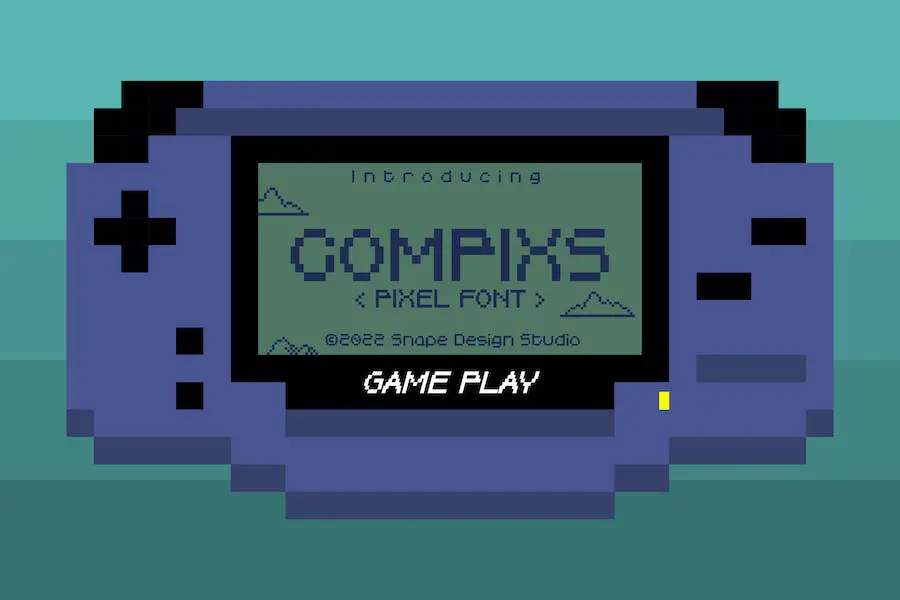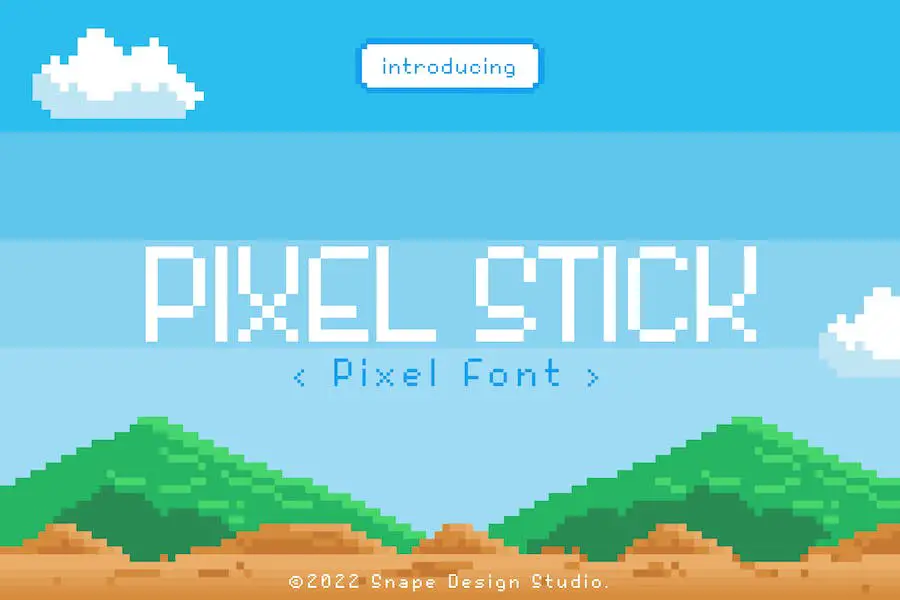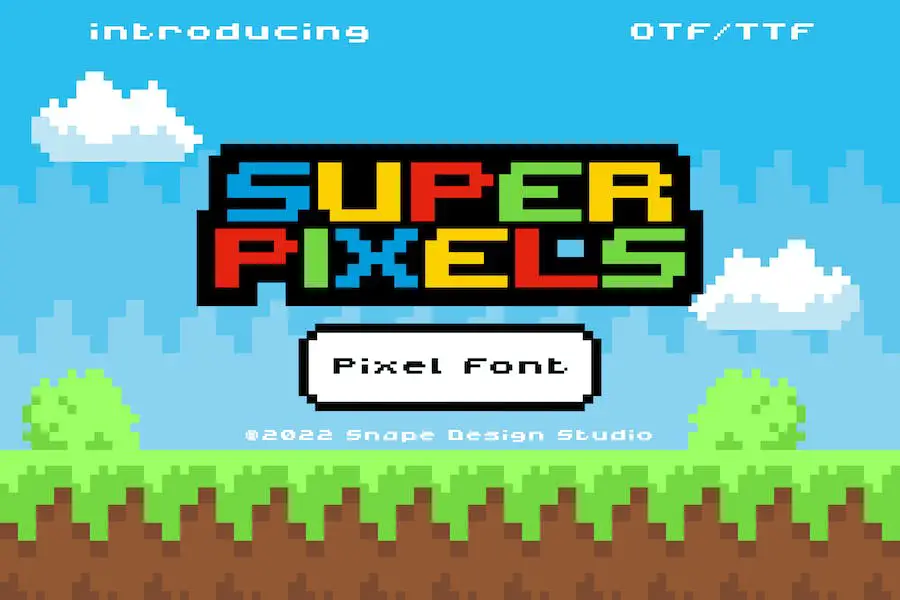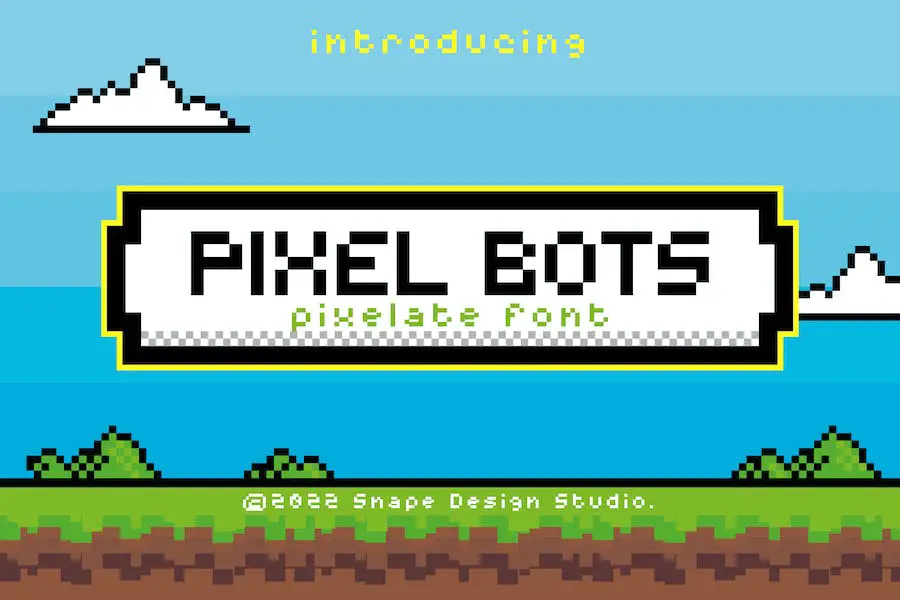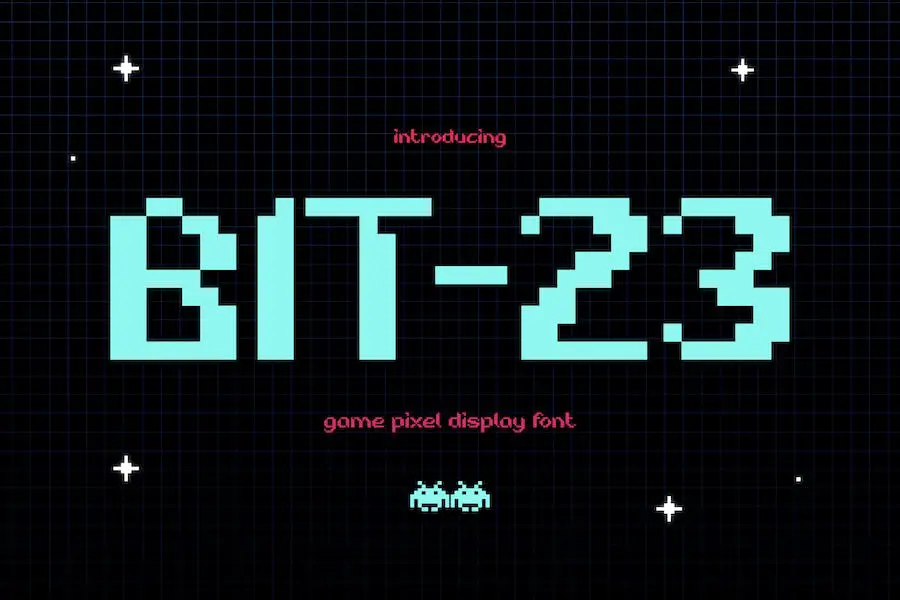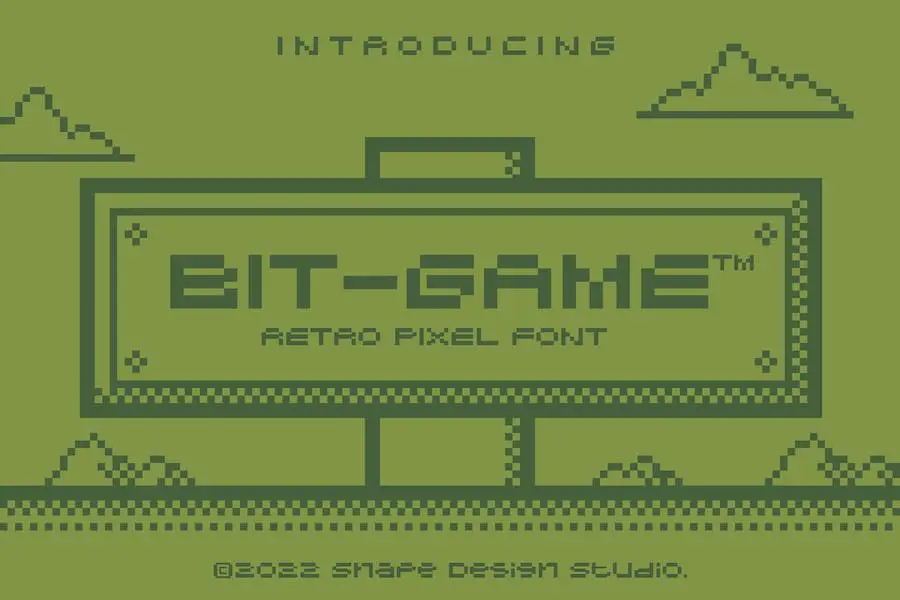
8 Bit Yazı Tipinden başkasına bakmayın! Bu blog yazısında 8 bitlik yazı tiplerinin dünyasını ve bunların tasarımlarınızı bir sonraki seviyeye nasıl taşıyabileceğini keşfedeceğiz. İster deneyimli bir grafik tasarımcı olun ister yeni başlıyor olun, bu yazı tipleri kesinlikle dikkatinizi çekecektir.
Şimdi "8 bitlik yazı tipleri tam olarak nedir?" diye merak ediyor olabilirsiniz. Peki, açıklayayım. 8bit yazı tipleri, retro video oyunlarının nostaljik çağından ilham alan yazı tipleridir.
Eski konsollarda klasik oyunlar oynayarak geçirilen saatleri hatırlatan pikselli karakterleri ve canlı renkleri düşünün. Bu yazı tipleri her türlü tasarıma benzersiz ve eğlenceli bir dokunuş katarak izleyicinin dikkatini anında çeker.
Bu yazıda 8 bitlik yazı tiplerinin dünyasına dalacağız ve kendi projelerinizde kullanabileceğiniz bazı inanılmaz örnekleri sergileyeceğiz.
Ayrıca bu yazı tiplerini kullanmanın, nostalji duygusu uyandırma yetenekleri ve çeşitli tasarım stillerinde çok yönlülükleri gibi faydalarını da tartışacağız. Birlikte bu 8 bitlik yazı tipi yolculuğuna çıkarken tasarım oyununuzun seviyesini yükseltmeye hazır olun!
En İyi Premium 8 Bit Yazı Tipleri
Tasarım projelerinize nostaljik bir dokunuş ve pikselli çekicilik mi katmak istiyorsunuz? En iyi premium 8 bit yazı tiplerinden özenle seçilmiş seçimlerimizden başka bir yere bakmayın. Tasarımlarınızı bir sonraki seviyeye taşıyacak mükemmel yazı tiplerini keşfetmek için bu makaleye dalın.
Para Ding Dong
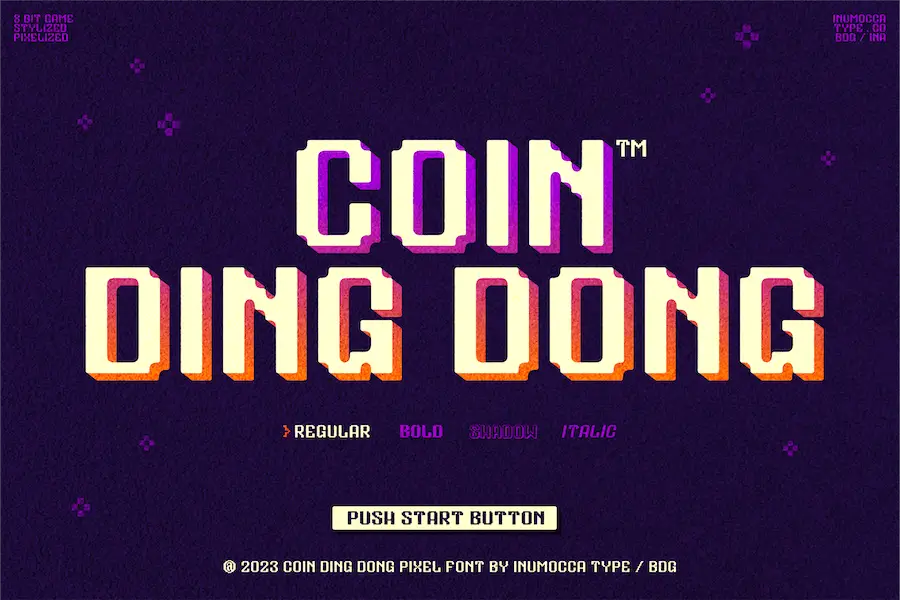
Coin Ding Dong, tasarım projelerinizi bir sonraki seviyeye taşıyacak muhteşem bir piksel yazı tipidir. Çok dilli karakterleri, benzersiz glifleri ve PUA kodlamasıyla bu yazı tipi sonsuz yaratıcı olanaklar sunar.
8 bitlik oyunların nostaljik dünyasından ilham alan Coin Ding Dong, güzel stilize edilmiş pikselleriyle sizi çocukluğunuza götürüyor. Tıpkı bir kumar makinesinde oynamak gibi, bu Google 8 Bit yazı tipi
eğlence ve heyecan dolu anıları geri getirir.
En iyi yanı Coin Ding Dong'un kolay olmasıdır
kullanmak. PUA kodlaması ile sunduğu tüm özel karakter ve sembollere sorunsuz bir şekilde erişebilirsiniz. Sınırlamalara elveda, sonsuz yaratıcılığa merhaba deyin.
Alpharush – retro oyun yazı tipi
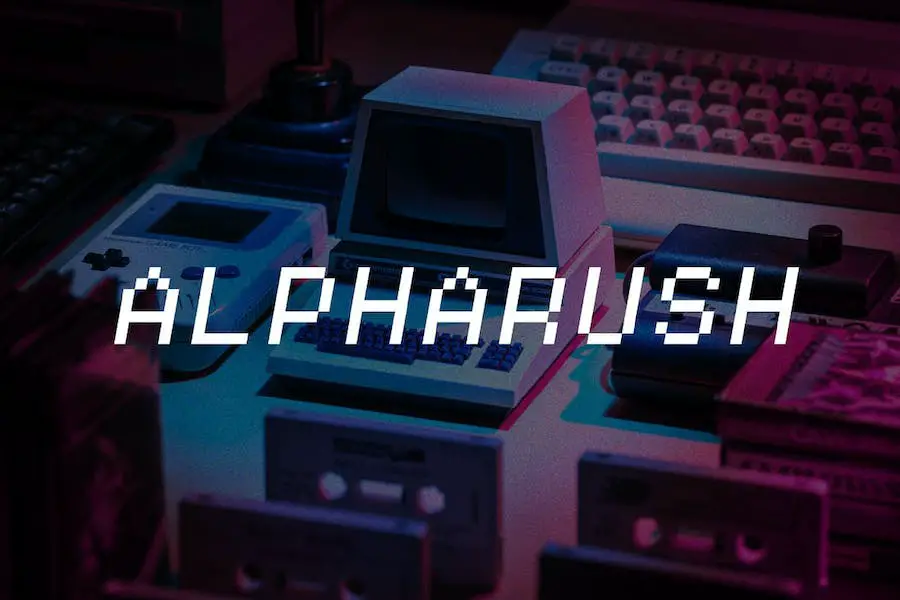
Alpharush – retro oyun yazı tipi, projelerini bir nostalji dokunuşuyla geliştirmek isteyen grafik tasarımcıları için harika bir seçimdir.
Bu yazı tipi, 80'lerin özünü yakalayan piksel sanatı ve 8 bitlik oyunlar için mükemmeldir. Retro bitmap stiliyle Alpharush çok yönlüdür ve nostaljik bir hava gerektiren her türlü tasarım projesi için mükemmeldir.
İster bir oyun üzerinde çalışıyor olun, ister vintage esintili posterler oluşturuyor olun, ister nostaljik bir logo tasarlıyor olun, bu Adobe 8 Bit yazı tipi ihtiyacınızı karşılar. Özelliklerine bakalım.
Alpharush'un öne çıkan özelliklerinden biri de 80'ler duygusunu uyandırabilmesidir. Retro estetiği ve pikselli çekiciliğiyle bu yazı tipi, kullanıcıları atari oyunlarının ve neon ışıkların altın çağına geri götürüyor.
İster nostaljik bir sanat eseri, ister sürükleyici bir oyun deneyimi yaratmak isteyin, Alpharush bunu size sunar.
Dalgalar TBM'si
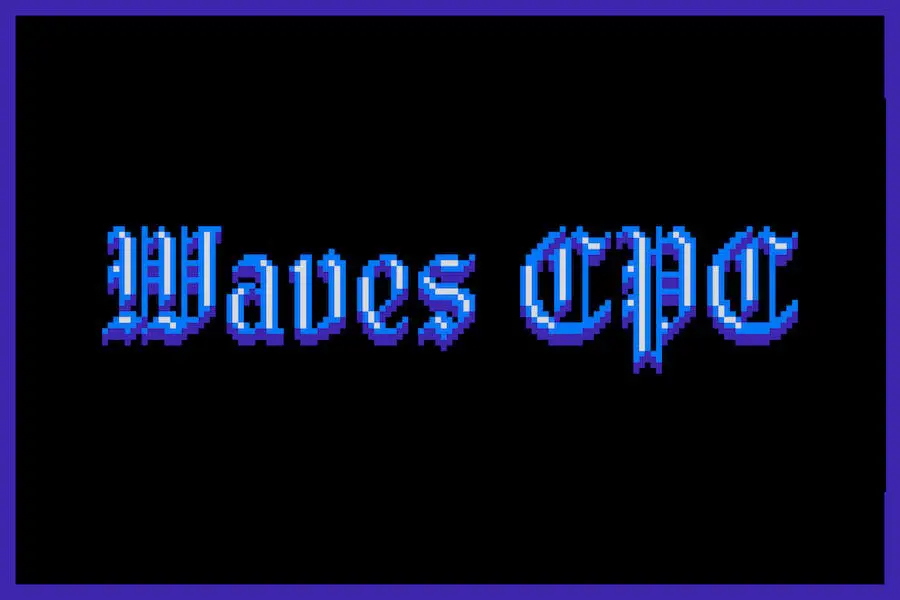
Waves CPC, şu anda geliştirme aşamasında olan bir piksel yazı tipi ailesidir. Basitleştirilmiş bir blackletter yazı tipini tasarımcının piksel sanatı deneyimiyle birleştirmek amacıyla oluşturuldu.
Yazı tipinin adı 8 bitlik müzikten, dalga formlarından ve gezegenimizin okyanuslarında bulunan devasa dalgalardan ilham almıştır. Yazı tipi ailesi şu anda üç üyeden oluşuyor ve gelecekte daha fazla ekleme yapılması planlanıyor.
Retro 8 bit estetiğin cazibesini siyah harfli tipografinin zarafeti ile birleştirir. Piksel sanat deneyiminin birleştirilmesi genel tasarıma benzersiz bir dokunuş katıyor. Word için bu 8 Bit yazı tipine yönelik daha fazla güncelleme ve eklemeler için bizi takip etmeye devam edin.
Sanspix
Sanspix, herhangi bir tasarım projesine benzersiz bir dokunuş katan retro piksel yazı tipi stilidir. Retro oyun tasarımı temasıyla logolar, posterler, kitap kapakları ve daha fazlası için mükemmel seçimdir.
Herhangi bir sorunla karşılaşırsanız yaratıcı destek sağlamaya hazırdır. Sanspix'i tasarımlarınıza dahil ederek yaratıcı fikirlerinize çarpıcı bir görünüm kazandırın.
Piksel Kart
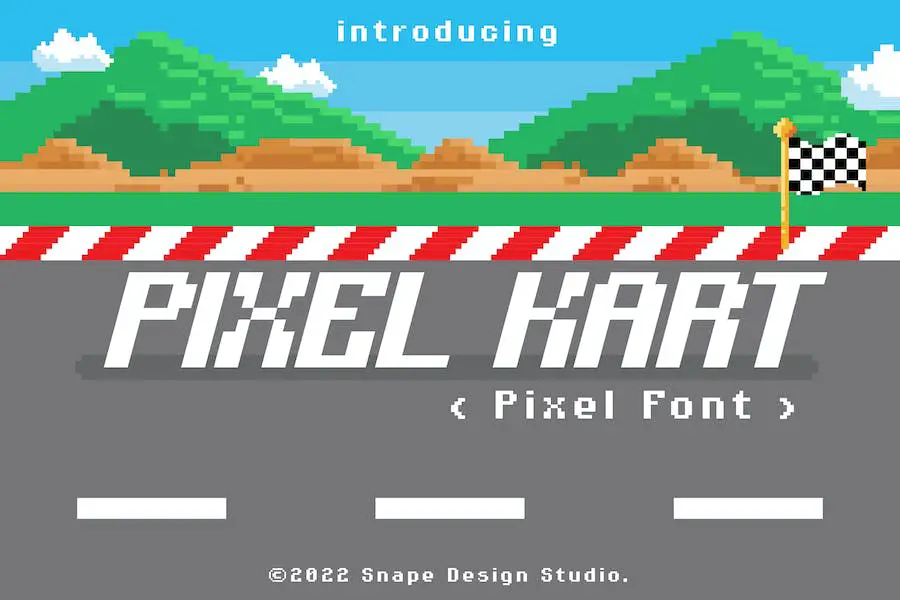
Pixel Kart, tasarımlarınızı klasik video oyunlarının nostaljik çağına götürecek havalı ve retro bir piksel yazı tipi stilidir. Hem otf hem de ttf dosya formatlarıyla bu yazı tipinin kullanımı kolaydır ve çoğu tasarım yazılımıyla uyumludur.